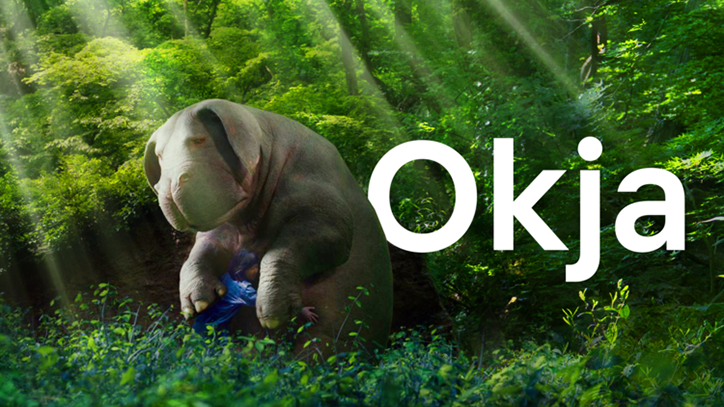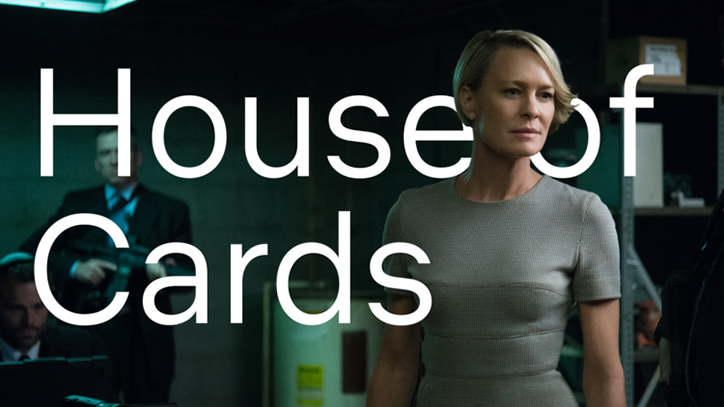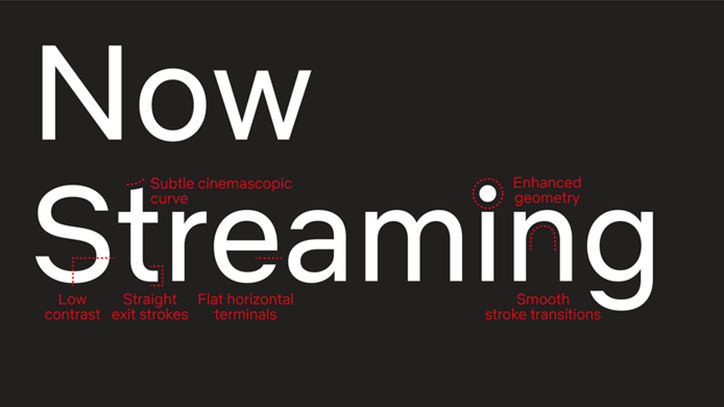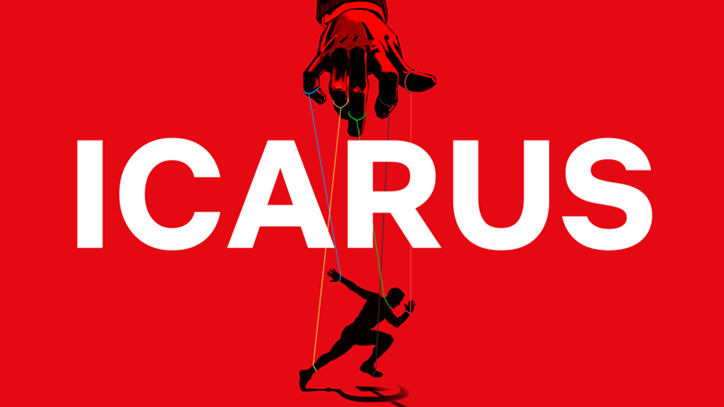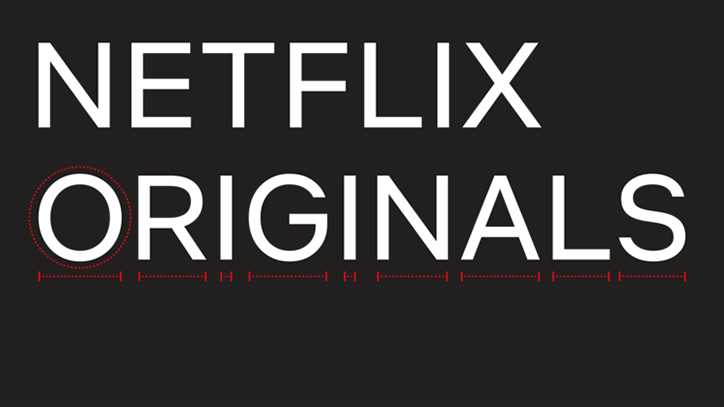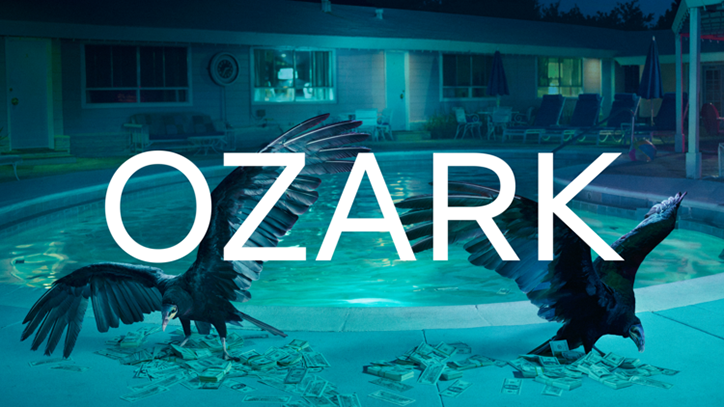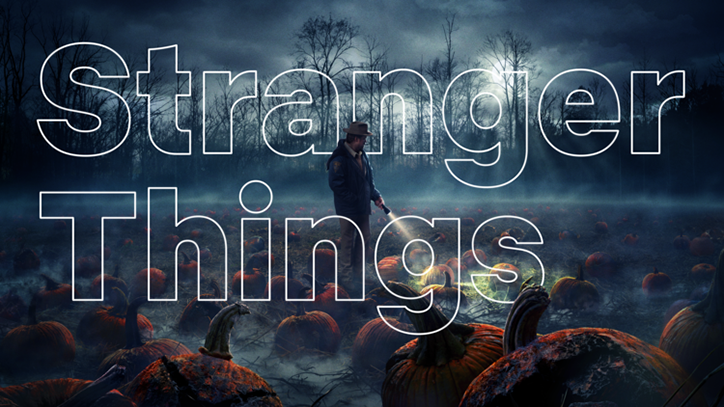
Netflix представил официальный шрифт Netflix Sans, который будет использоваться во всей айдентике бренда. Разработкой новых текстовых очертаний занималась собственная команда дизайнеров Netflix в сотрудничестве с Dalton Maag.
Представители Netflix поясняют, решение создания собственного шрифта было обусловлено несколькими причинами, главные из которых: высокие затраты на использование шрифта Gotham, а также стремление к абсолютной уникальности бренда.
Дизайнеры отмечают прагматичность и функциональность нового шрифта, подчеркивая, что выглядит он довольно «кинематографично, компактно, чисто и нейтрально».